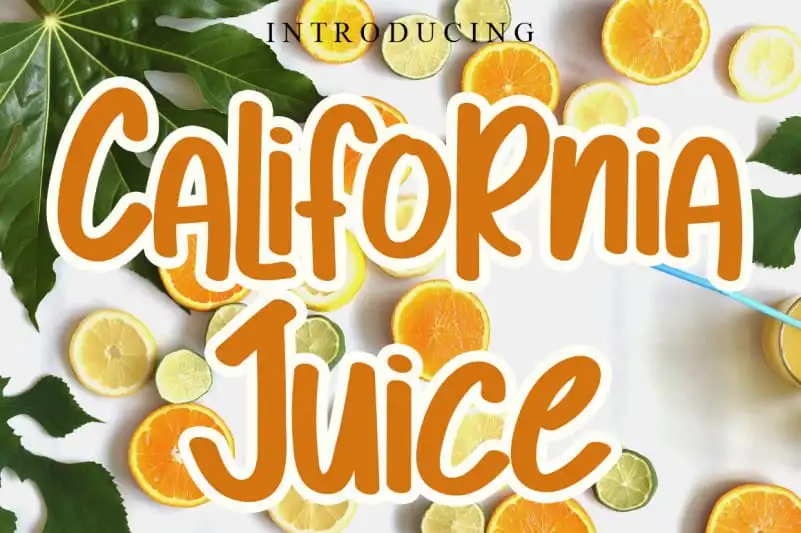
California Juice Display Font – Download Grátis
Aqui está uma versão contendo 2 parágrafos curtos, para descrever a fonte ‘California Juice Display Font’ de maneira envolvente e natural, como se estivesse escrito por um blog sobre recursos gráficos: Sorria com sua escrita. California Juice Display Font é uma mistura encantadora de fontes modernas, que transformará suas criações em verdadeiros destelhos visuais. Com seus traços simples mas poderosos, essa fonte criará o impacto necessário para tornar seus designs ainda mais atraentes, num piscar de olhos. Para quem procura algo fresco e divertido, California Juice Display Font é uma excelente escolha. Seu design encantador combina características modernas com uma leveza que se assemelham à suavidade do sumo de laranja. Sem dúvida alguma, ela será um grande aliado para aqueles em busca de um visual que não pode ser ignorado no seu próximo projeto gráfico.